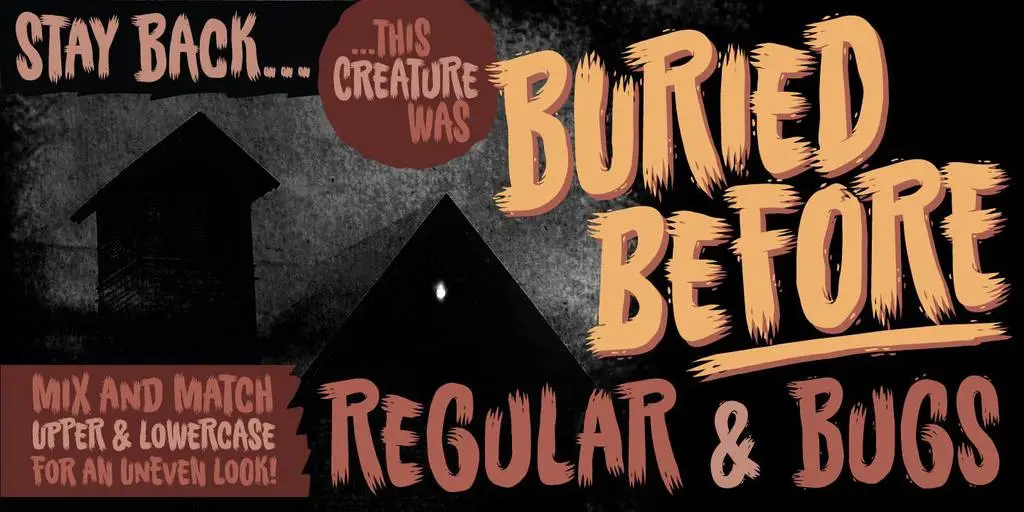
A Buried Before Font Family é uma fonte Brush que surge justamente no momento perfeito para suas necessidades de Halloween. Inspirada na estética do terror vintage e com um brilho adorável que remete a desenhos de papel machê, esta fonte vem em versões Regular e Bugs, adicionando um toque descontraído e divertido à sua identidade visual. A Buried Before é uma escolha perfeita para criar títulos assustadores ou personalizados para seus projetos. Ela traz a beleza vintage de desenhos antigos, embalada num estilo que parece ser um pouco escondido, dando uma sensação misteriosa e única aos teus materiais. Se você está buscando um grampo ideal para trabalhos como letras grandes em cartazes ou até mesmo para criar aquele toque especial nos websites, a Buried Before é o ideal. Com seus detalhes engraçados ao redor das letras que lembram desenhos infantis, ela ganha ainda mais vida e personalidade. Estamos certamente felizes com esta fonte, uma bela combinação de estilos que tornarão sua identidade visual única e atraente. Em breve, você pode encontrar Buried Before em seu repositório de fonts favorito!